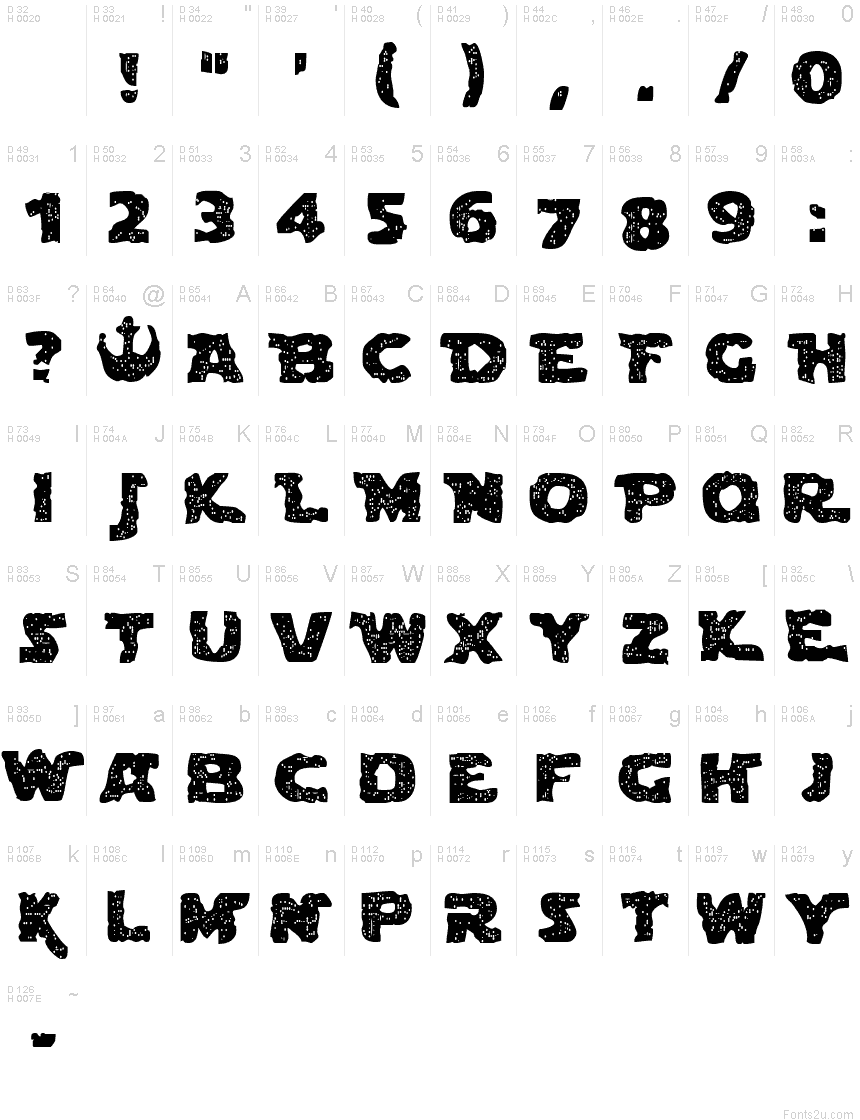
خط Blown Droid من تصميم Phillip Andrade هو خط عرض (display) مجاني بلمسة مهترئة، يتميز بحروف ضخمة تشبه المطاط ومليئة بالفجوات والندوب. الأشكال السوداء الجريئة تبدو وكأنها منحوتة يدوياً وغير مستقرة، مما يعطي انطباعاً بأنها تهتز على الصفحة، ويمنح كل كلمة طاقة خشنة تجمع بين الخيال العلمي وأسلوب الجرونج بشكل لا يمكن تجاهله. عند النظر عن كثب، تضفي الفراغات المنقطة والخطوط غير المنتظمة طابعاً ملموساً يكاد يبدو منصهراً، مما يجعل النص بارزاً وقابلاً للقراءة في الأحجام الكبيرة.
استخدم خط Blown Droid للعناوين والشعارات في واجهات الألعاب، وملصقات الرعب أو الخيال العلمي، وعلامات تجارية لملابس الشارع، ومنشورات الحفلات، وأغلفة الألبومات، وصور مصغرة لمقاطع يوتيوب. هذا الخط المجاني يتألق عند استخدامه بحجم كبير وخط عريض، بينما يمكن تنسيق النص التكميلي بخط هندسي sans-serif نظيف من عائلة Blown Droid أو أي خط نظام أساسي لضمان التباين والوضوح.
Blown Droid